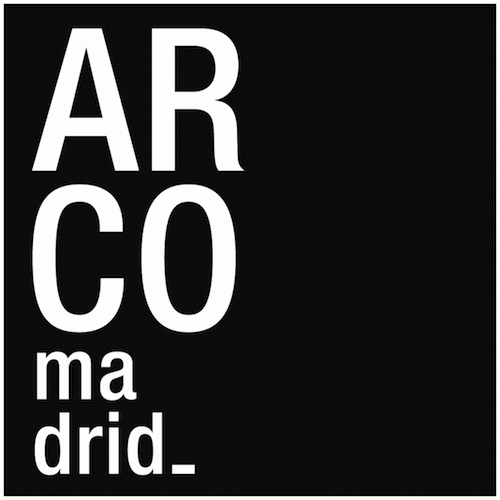
Foro de Tipografía Tipografia de ARCO Madrid el 02.02.2017 a las 00:18 por barbaraaandres · 2 comentarios Seguir este tema Dejar de seguir este tema 3 seguidores Hola! Necesito ayuda con esto; alguien me puede decir la tipografia o una similar a la que aparece en la identidad gráfica de ARCO? Mil gracias! Comentar Me gusta
Como bien indica @oli_s tiene toda la pinta de ser una «Helvetica Condensed Semibold».
Yo diría que es una Helvetica Condensed Semibold. Yo tengo la Neue Condensed Bold y es un poco más robusta.